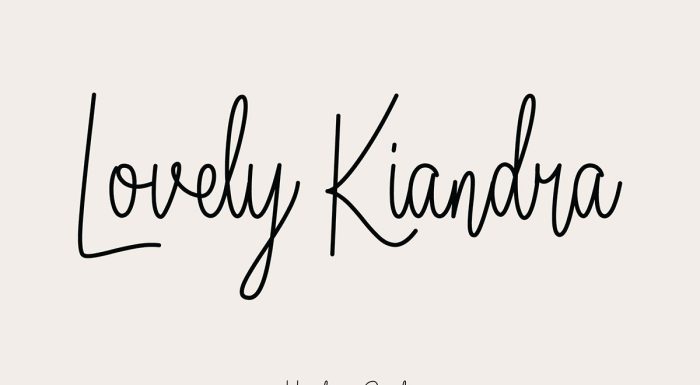
فونت Lovely Kiandra انگلیسی
| ⭐ مجموعه فونت | دانلود فونت انگلیسی کیاندرای دوست داشتنی Font Lovely Kiandra |
| ⭐ توضیحات | Lovely Kiandra فونت اسکریپت امضا است. زیبا و سرگرم کننده، این فونت برای نوشتن دعوت نامه عروسی، کارت، یا هر طرح دیگری که نیاز به لمس سفارشی دارد، ایده آل است. |